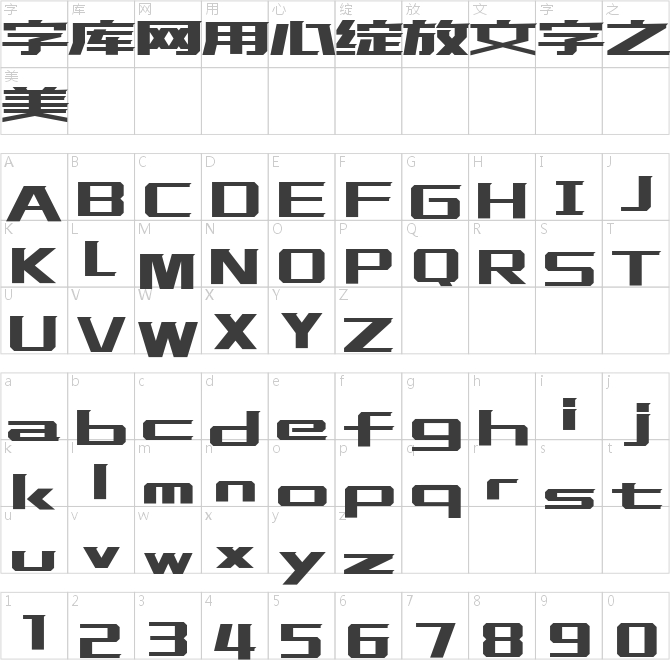
設(shè)計(jì)師愛(ài)心體1號(hào)字 詳情頁(yè)
字體名稱(chēng): 設(shè)計(jì)師愛(ài)心體1
設(shè)計(jì)師愛(ài)心體1號(hào)字
設(shè)計(jì)師愛(ài)心體1號(hào)字介紹
【設(shè)計(jì)師愛(ài)心體1號(hào)字】
【設(shè)計(jì)師愛(ài)心體1號(hào)字】基于中華人民共和國(guó)GB2312-80字符集漢字部分標(biāo)準(zhǔn),TrueType格式,共收容漢字6763個(gè),英文及標(biāo)點(diǎn)等常用字符251個(gè)。
【作者信息】
設(shè)計(jì)師愛(ài)心體1號(hào)字設(shè)計(jì)師團(tuán)隊(duì):
劉兵克、李買(mǎi)、劉金營(yíng)、劉志明、班小許、熊偉、周登恒、高晗、符重慶、李雪萍、武瑞鑫、黃婕妮
【關(guān)于困境兒童】
《設(shè)計(jì)師愛(ài)心體1號(hào)字》是為了能夠更好地服務(wù)困境兒童,讓他們的未來(lái)有更多的可能性,彌補(bǔ)他們學(xué)習(xí)生活中藝術(shù)教育的缺失,字體設(shè)計(jì)師劉兵克與歷下區(qū)未成年人救助保護(hù)中心合作,為歷下區(qū)困境兒童設(shè)立設(shè)計(jì)師公益基金,于20216月發(fā)布。
【關(guān)于設(shè)計(jì)師愛(ài)心體1號(hào)字】
設(shè)計(jì)師愛(ài)心體,源自“困境兒童”公益活動(dòng)。由設(shè)計(jì)師劉兵克發(fā)起這個(gè)項(xiàng)目,并設(shè)計(jì)最初的字形規(guī)范及基本部首,最終,一套好用且免費(fèi)的中文字體“設(shè)計(jì)師愛(ài)心體1號(hào)字”誕生,并在20216月發(fā)布。
在未來(lái)的日子里,劉兵克將會(huì)帶領(lǐng)他的團(tuán)隊(duì)持續(xù)開(kāi)發(fā)多套字庫(kù)作品,設(shè)計(jì)師愛(ài)心體1號(hào)字只是開(kāi)始,未來(lái)會(huì)出現(xiàn)設(shè)計(jì)師愛(ài)心體2號(hào)字、3號(hào)字、4號(hào)字、5號(hào)字……而每一套愛(ài)心字庫(kù),將會(huì)幫助和捐助予不同的受助對(duì)象。
“設(shè)計(jì)師愛(ài)心字庫(kù),一方面可以讓設(shè)計(jì)師有更多的字庫(kù)選擇,另一方面,也讓大家通過(guò)對(duì)愛(ài)心字庫(kù)的捐助與下載,為公益事業(yè)獻(xiàn)上愛(ài)心,這是一件美好和溫暖的事情。我非常期待1號(hào)字能夠得到大家的認(rèn)可,說(shuō)實(shí)話,也更期待1號(hào)字能完成目標(biāo)捐款金額。如果能夠順利完成,這會(huì)給我們帶來(lái)更大的勇氣和信心,愛(ài)心字庫(kù)這份事業(yè),我們會(huì)更有勁頭的做下去!”
劉兵克
設(shè)計(jì)師愛(ài)心體1號(hào)字效果圖